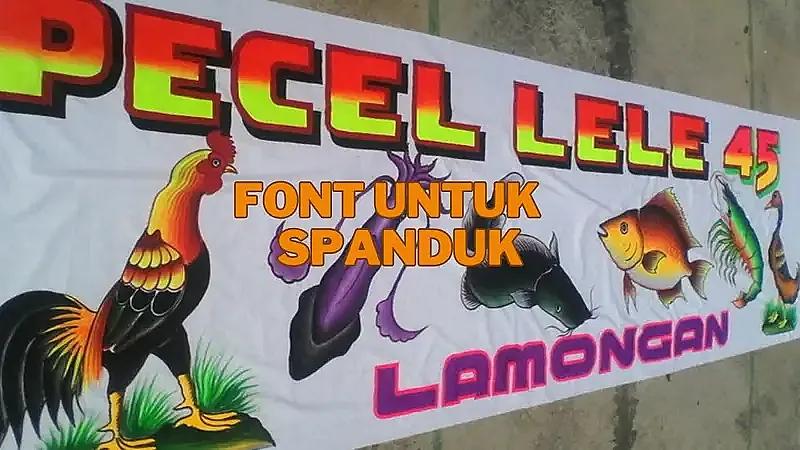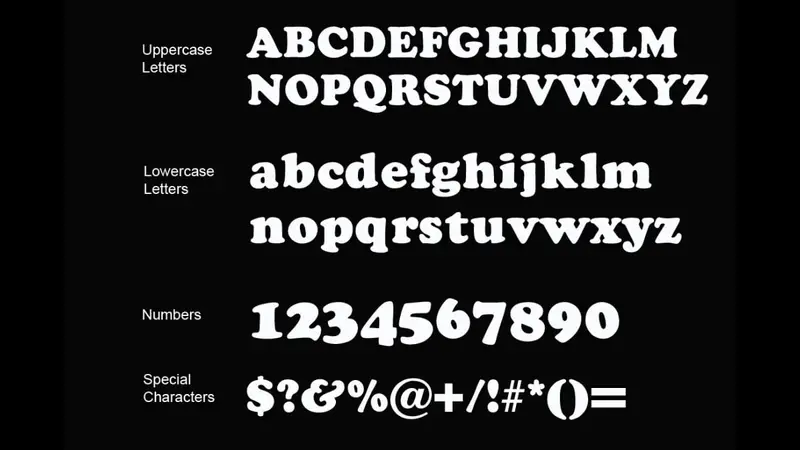
Kenali 8 Jenis Font Untuk Spanduk, Bikin Spandukmu Makin Sedap Dipandang!
Pemilihan font untuk spanduk tidak boleh sembarangan, sebab dapat merusak estetika dan tampilannya secara keseluruhan. Bukannya membuat orang tertarik, justru diabaikan dan dianggap mengganggu pemandangan. Berhubung pilihan font sangat banyak, mana sih yang bisa membuat spanduk kamu semakin eye catching sehingga menarik semua mata untuk melihatnya? Ini dia rekomendasi lengkapnya!
Font keren untuk spanduk yang pertama adalah cooper black yang termasuk dalam jenis huruf Serif. Font ini dinamai berdasarkan penemunya, yaitu Oswald Bruce Cooper, pada 1922. Jenis font Cooper Black sendiri baru populer pada tahun 60 – 70 an dan hingga kini menjadi salah satu fonta paling favorit.
Karakteristik huruf ini tebal, estetik, tapi mencitrakan kesan santai. Biasanya memang dipilih untuk sesuatu yang bersifat santai dan menghibur. Dalam spanduk, bisa kamu pilih untuk informasi event atau promosi khusus. Cooper Black juga menjadi salah satu font untuk spanduk di Canva. Jadi tidak perlu menginstalnya manual bila menggunakan aplikasi tersebut.
Arial Black menjadi rekomendasi font berikutnya untuk spanduk kamu. Tidak perlu download font untuk spanduk lagi jika memilih jenis huruf yang satu ini karena menjadi salah satu setting-an default di berbagai aplikasi. Arial Black sendiri merupakan versi tebal (bold) dari Arial dan termasuk golongan huruf sans serif.
Karakteristik huruf ini adalah tegas dan sederhana. Cocok untuk kamu sematkan di spanduk yang berisi pengumuman atau sesuatu yang sifatnya formal dan semi formal. Font ini kurang sesuai kalau kamu jadikan sebagai pilihan huruf untuk spanduk hiburan karena akan menjadikannya tampak membosankan.
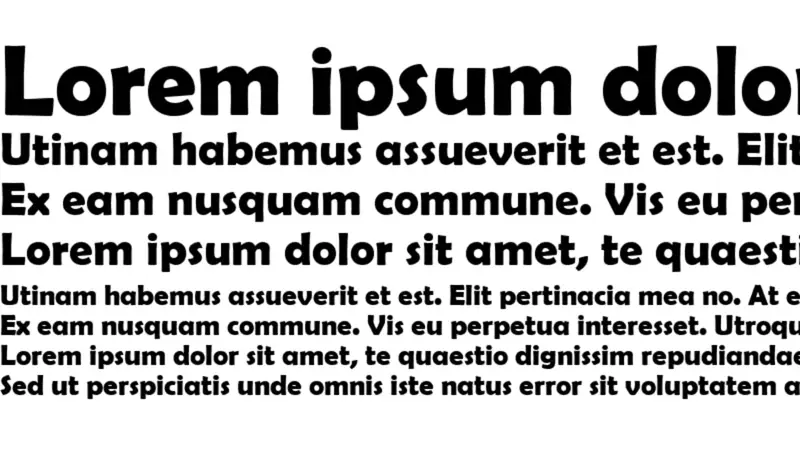
Font selanjutnya adalah Berlin Sans FB yang didesain pada akhir abad 20-an, sehingga masih cukup muda. Lucian Berhard yang menciptakannya, kemudian disempurnakan oleh Matthew Butterick dan David Berlow. Berlin Sans FB merupakan jenis font keren untuk logo karena memiliki karakteristik tebal, tegas, dan eye catching.
Kamu bisa menggunakannya sebagai font untuk spanduk bengkel untuk memberi kesan bersahabat tapi tetap dapat diandalkan dalam menangani urusan kendaraan bermotor. Berlin Sans FB juga bisa digunakan dalam spanduk lain yang bersifat non formal dan semi formal seperti informasi event pekan raya.
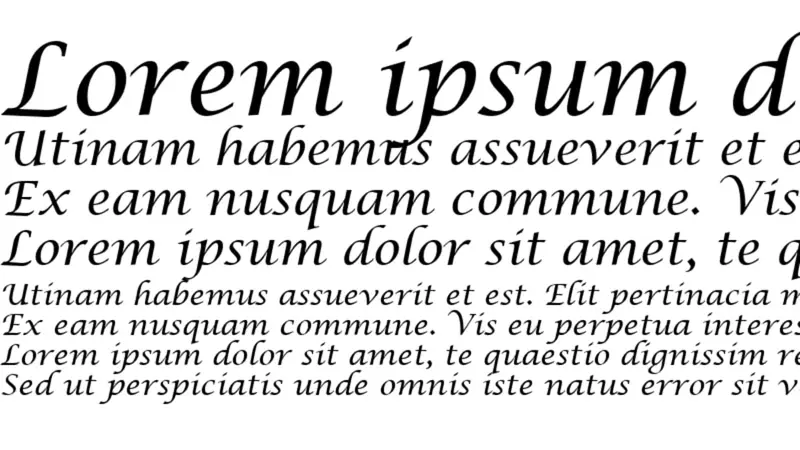
Jika kamu mencari font untuk spanduk Ramadhan, Lucida Calligraphy menjadi piihan yang paling tepat. Typeface ini memiliki karakteristik bagaikan ukiran tulisan tangan alias kaligrafi. Estetik, dekoratif, dan menonjolkan seni tinggi. Font ini juga sudah termasuk tua sehingga masuk dalam paket default font di berbagai aplikasi tanpa perlu mengunduhnya secara manual.
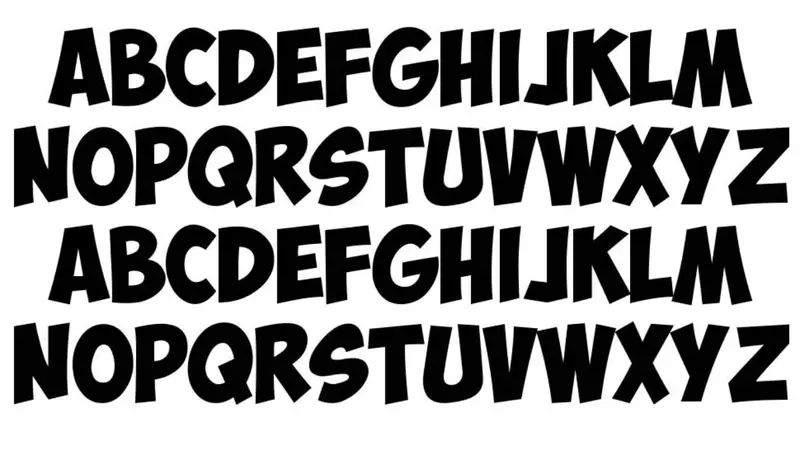
Obelix Pro merupakan jenis typeface yang cocok menjadi font untuk spanduk makanan. Font yang satu ini umumnya digunakan pada komik, karena mempunyai bentuk tebal dan tampak santai. Mengaplikasikannya pada spanduk makanan akan membuatnya jadi lebih menarik, apalagi jika disertai dengan desain berupa gambar-gambar menu makanan bertipe vector yang sangat lucu.
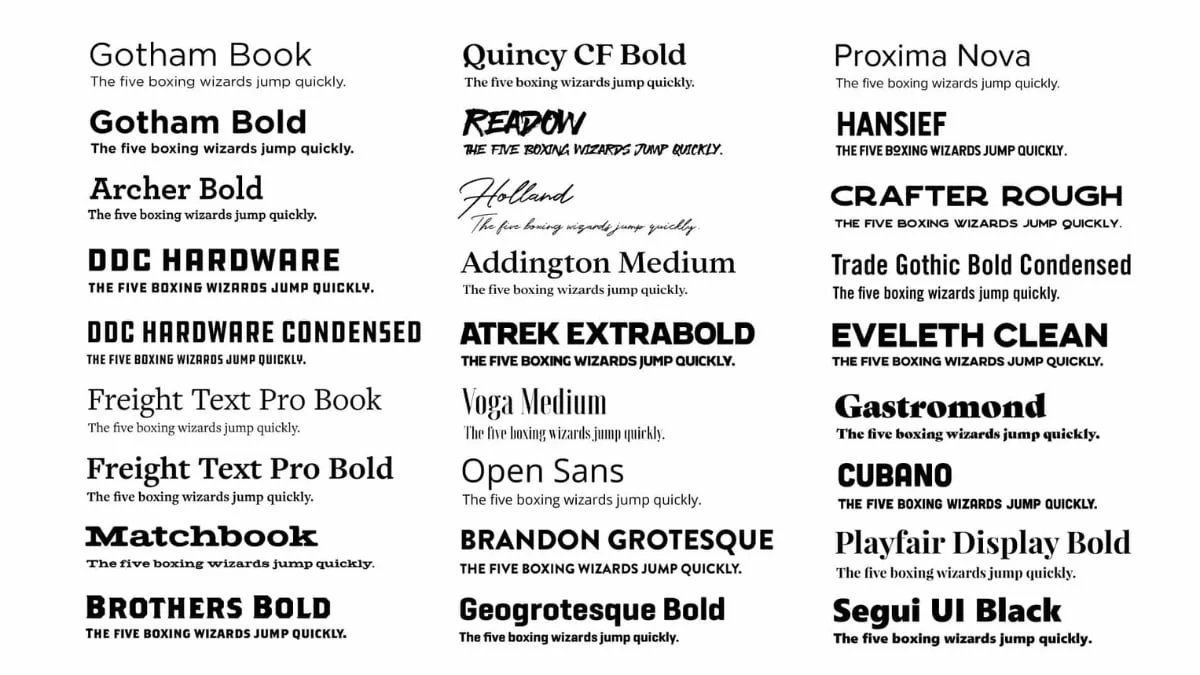
Font untuk spanduk berikutnya adalah typeface modern yang terdiri dari berbagai jenis huruf baru ditemukan. Contohnya, Anona, Seismic, Kinfolk, TA Modern Times. Kelompok fonts ini harus kamu unduh manual karena diciptakan dan dikembangkan pihak ketiga yang tidak bekerja sama resmi dengan Windows yang membuat kelompok fonts ini bukan setting-an default.
Karakteristik kelompok font modern ini adalah sederhana tapi estetik. Ada yang berjenis Serif, kaligrafi, dan lainnya. Mengaplikasikannya pada spanduk akan membuat umbul-umbul jadi semakin sedap dipandang. Salah satunya cocok untuk dipakai sebagai font spanduk pecel lele. Font modern sendiri ada yang gratis, tapi ada pula yang berbayar.
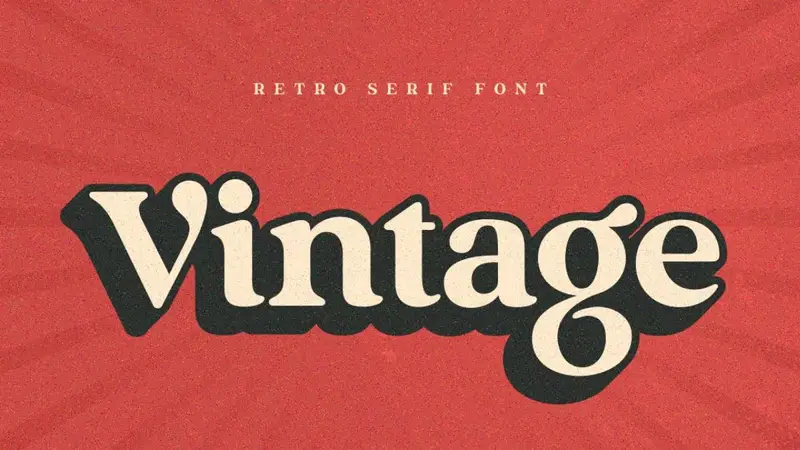
Selanjutnya ada kelompok typeface retro atau vintage. Karakteristik utamanya tentu klasik, sehingga membangkitkan keinginan untuk bernostalgia. Selain itu juga memberi kesan elegan dan berkelas. Biasanya diutamakan untuk menjadi fonts nama/merek produk maupun suatu tempat yang dipromosikan. Fonts ini bisa diaplikasikan pada berbagai jenis ukuran spanduk untuk kebutuhan formal hingga informal.
Kamu bisa membeli paket vintage typeface yang biasanya berisi lebih dari 20 jenis font dari pihak ketiga, kemudian menginstalnya untuk mendesain spanduk kamu. Contoh fonts retro antara lain: Roca, Ephemera Fascia, Black Drama dan lain-lain. Jika terlalu mahal, kamu bisa membeli dan mengunduhnya satuan dengan memilih font yang paling dibutuhkan.
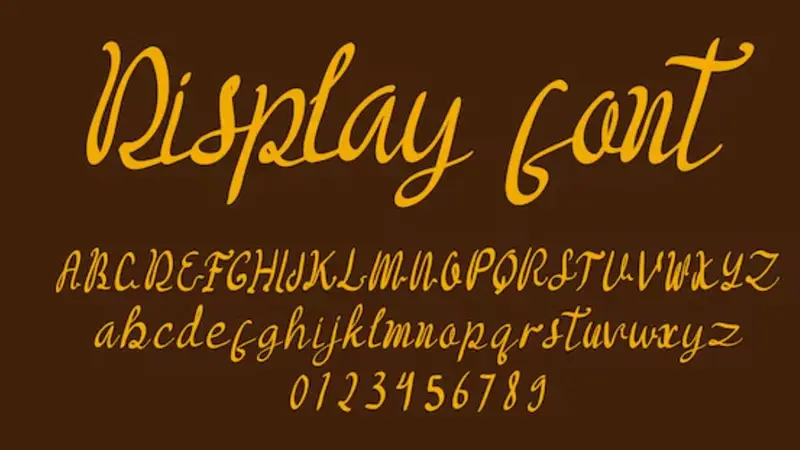
Berikutnya ada kelompok typeface yang cocok untuk berbagai jenis bahan spanduk untuk tujuan penggunaan pengumuman event, promosi produk, maupun kepentingan lainnya. Tidak lain adalah jenis script dan display font yang menampilkan kesan tulisan tangan dengan estetika dan cita rasa seni tinggi. Ada banyak jenisnya, seperti Restrike, Rigidity, dan banyak lagi.